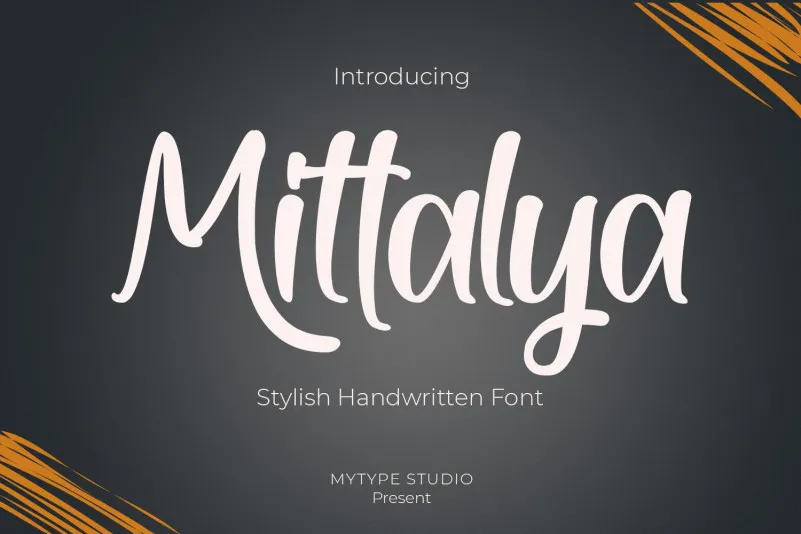
Afonte ‘Mittalya Font’ é uma elegante escolha para aqueles que desejam adicionar um toque de sofisticação a seus projetos digitais. Trata-se de uma tipografia script refinada e moderna, com um olhar antenado às tendências da marca atual. Suas linhas fluidas e detalhes meticulosamente elaborados oferecem um ar elegante e sofisticado que se destaca em diversas aplicações, incluindo logotipos, marcas de identidade, convites, embalagens de papel, design para casamentos, posts nas redes sociais e muito mais. É uma fonte perfeita para aqueles que buscam uma personalização única em seus projetos digitais.